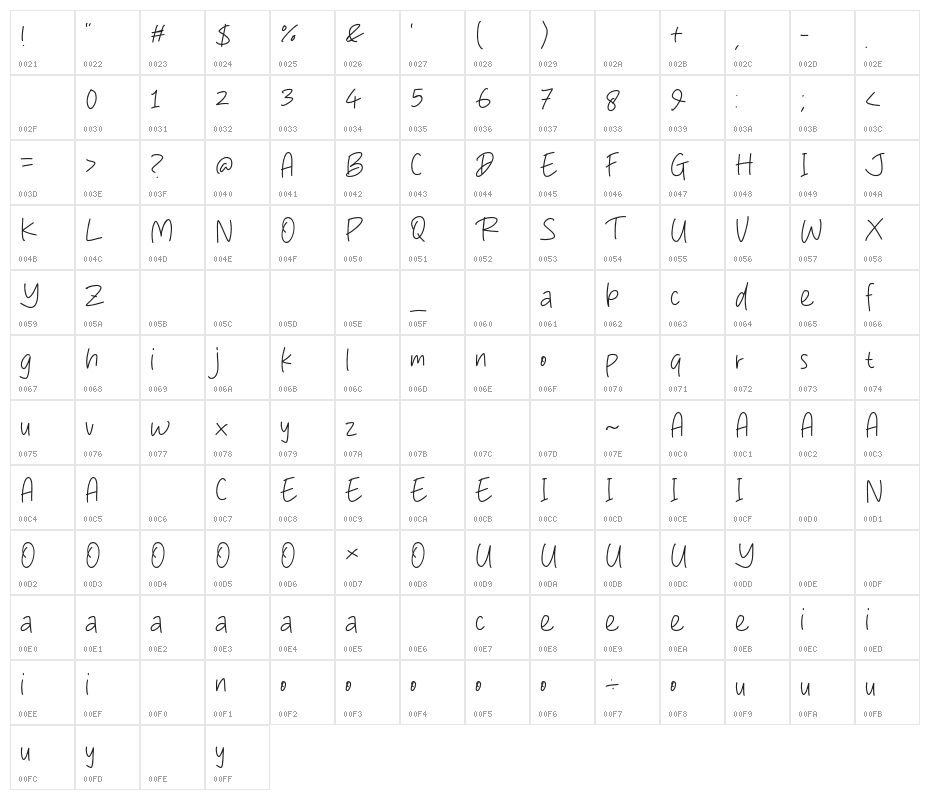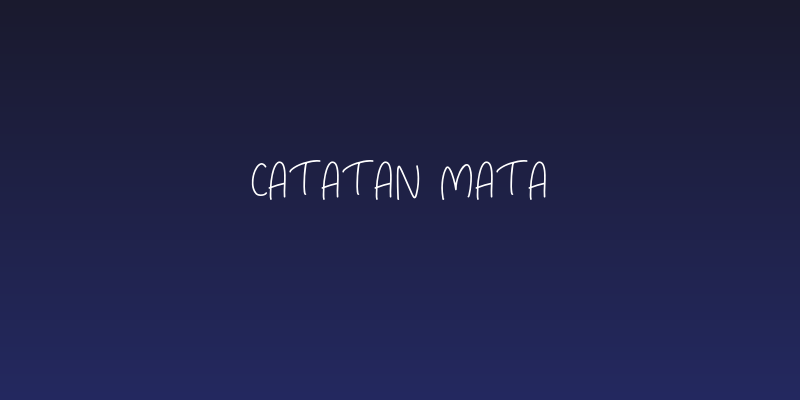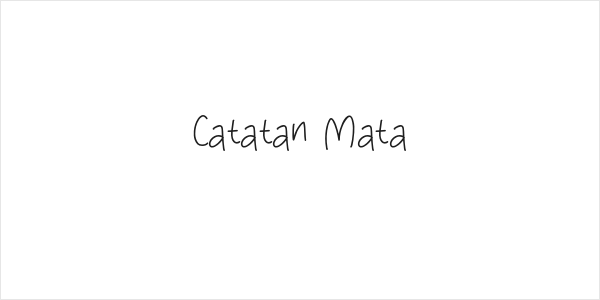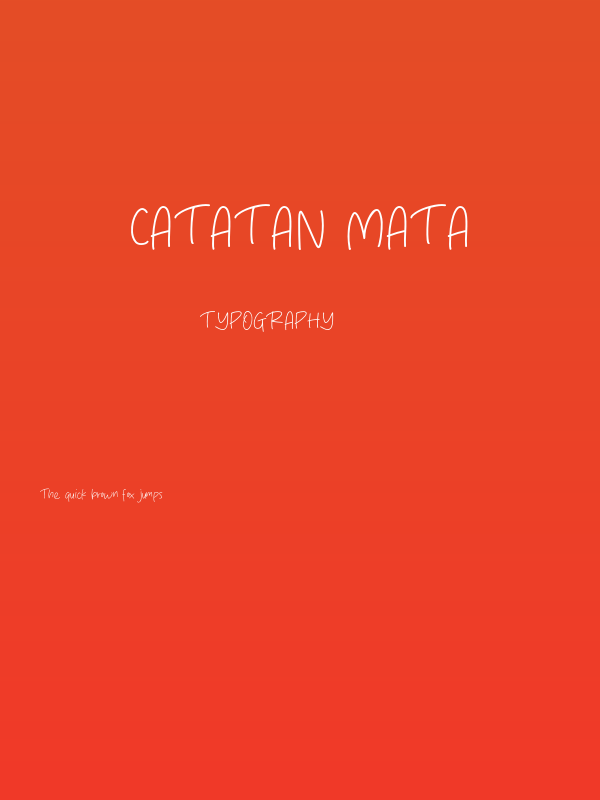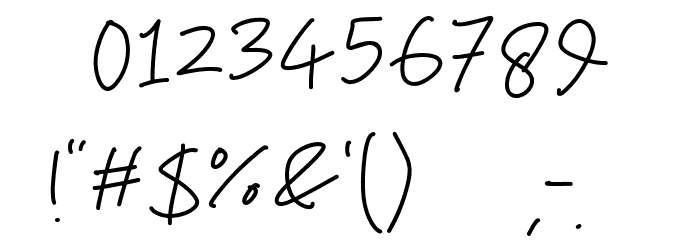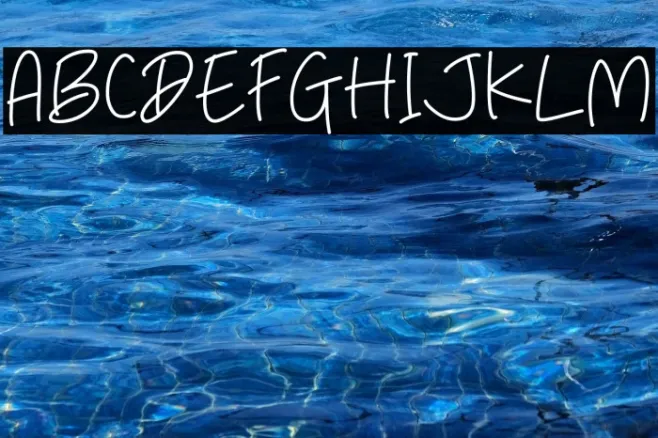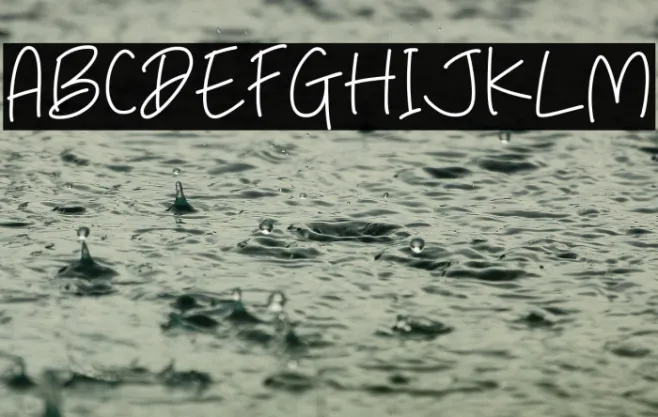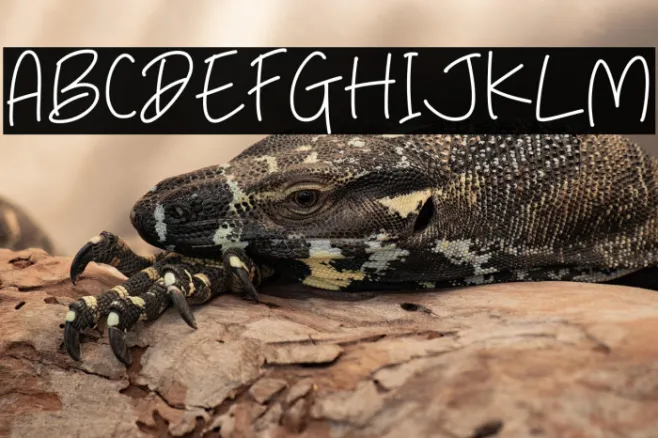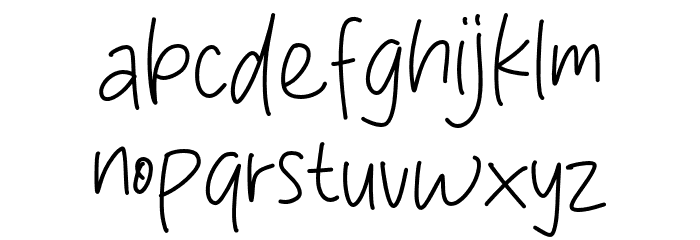
Catatan Mata Font
| Gesamtstil | Casual, Playful |
| Anwendungsfall | Invitations, Personal notes, Creative branding |
| Vorgeschlagene Projekte | Ideal for personal notes, invitations, creative branding, and informal communications. |